Как оформить таблички кабинетов в офисе и учебном учреждении
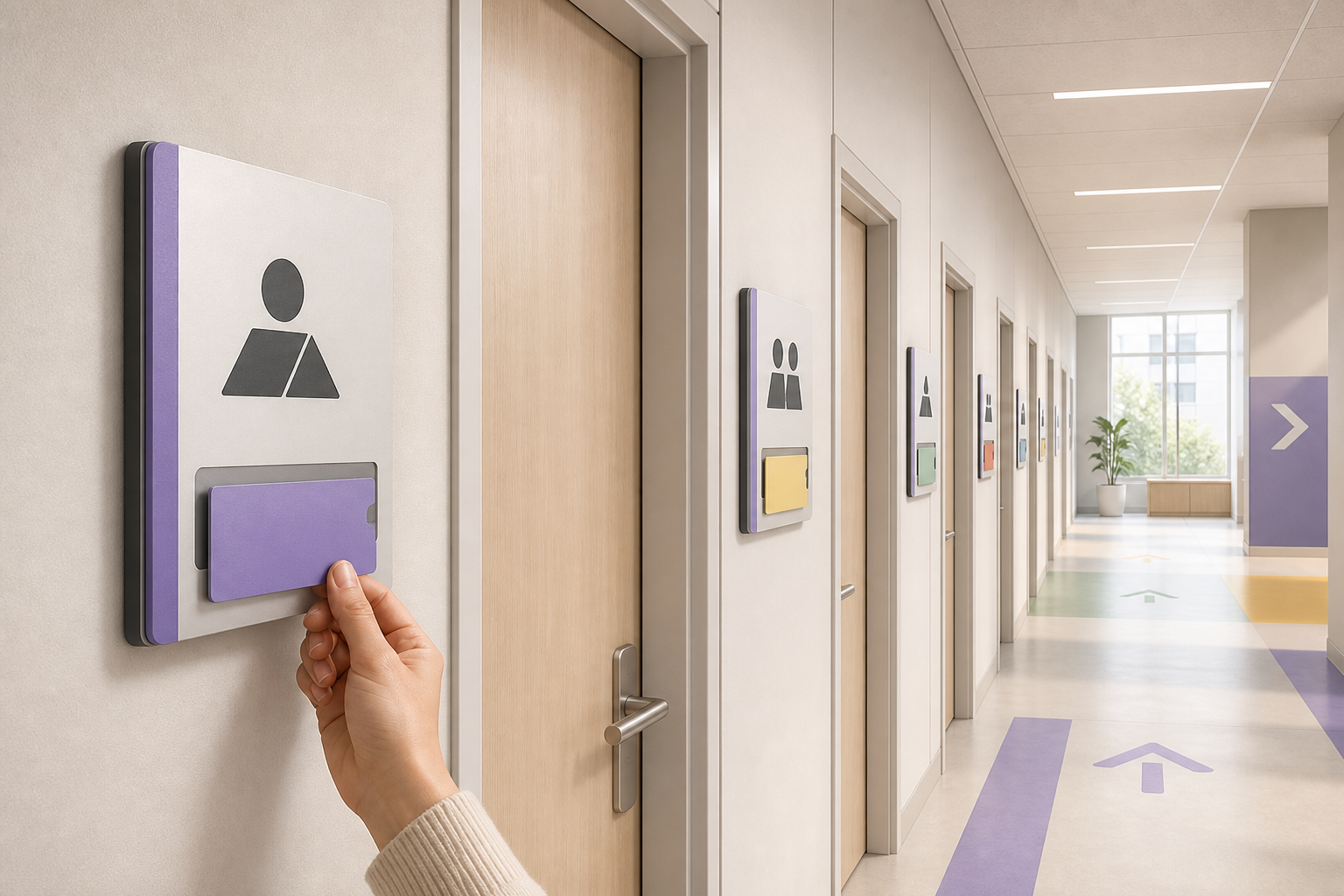
Таблички кабинетов оформляют так, чтобы посетитель сразу понял назначение помещения, легко прочитал название с расстояния и не перепутал дверь с соседней. Для этого заранее определяют текст, иерархию информации, размер, контраст, шрифт, материал и способ крепления. Ниже — практический порядок проектирования для офиса, школы, колледжа или вуза.
Зачем нужна продуманная табличка кабинета
Табличка кабинета выполняет сразу три задачи: сообщает, что находится за дверью, поддерживает навигацию по зданию и формирует визуальный образ организации. Если надпись заметна, кратка и выдержана в общей системе, человеку не приходится останавливаться у каждой двери или обращаться к сотрудникам за подсказкой. Поэтому это не просто декоративная наклейка, а элемент информационного дизайна.
Для офиса важны деловой характер, аккуратность и возможность быстро менять данные о сотрудниках или отделах. Для школы и другого образовательного учреждения на первом месте оказываются понятность, дружелюбная подача и единая логика обозначений: номер кабинета, название предмета, кафедра, лаборатория или служебная функция должны читаться одинаково на всех этажах.
Соберите систему помещений до начала дизайна
Начинайте не с выбора красивого шрифта, а с инвентаризации дверей. Составьте список всех помещений, проверьте написание названий, номера этажей и кабинетов, а также решите, какие данные должны обновляться. Такая подготовка предотвращает ситуацию, когда часть дверей оформлена по одному шаблону, а часть — случайными табличками разных размеров и цветов.
- Разделите помещения на группы: рабочие кабинеты, переговорные, классы, лаборатории, административные и технические зоны.
- Определите обязательные сведения: номер, название, должность, фамилия сотрудника или режим доступа.
- Зафиксируйте единый порядок строк, например сначала номер, затем назначение помещения, затем дополнительная информация.
- Отметьте двери, где требуется двусторонняя информация: свободно или занято, открыто или закрыто, вход для посетителей.
- Предусмотрите замену отдельных элементов, если сотрудники, кабинеты или расписание могут меняться.
Выберите размер, материал и крепление
Размер таблички зависит от длины текста, ширины дверного полотна и расстояния, с которого посетитель должен прочитать надпись. Для короткого номера кабинета достаточно компактного формата, а длинному названию отдела или кафедры понадобится больше ширины либо две строки. Не уменьшайте буквы только ради сохранения маленького размера: читаемость важнее экономии площади.
Материал выбирают по условиям эксплуатации. В сухом офисе подойдут пластик, акрил, композитная панель, металл или плотная самоклеящаяся плёнка. В школе и вузе особенно важны устойчивость к частому контакту, простота очистки и отсутствие острых краёв. Для временных мероприятий удобны картонные или пластиковые вставки, которые можно быстро заменить без переделки всей основы.
- Используйте матовую поверхность, если рядом есть окна, светильники или стеклянные двери.
- Выбирайте жёсткую основу для крупных настенных указателей и табличек в местах с интенсивным движением.
- Закладывайте безопасное крепление: ровное, устойчивое и не мешающее открыванию двери.
- Проверяйте, можно ли снять табличку без повреждения поверхности, если помещение арендуется.
- Согласуйте способ крепления с материалом двери: клей, дистанционные держатели, винты или магнитная система подходят для разных оснований.
Что выбрать для офиса
В офисе хорошо работает сдержанная табличка с логотипом или фирменным цветовым акцентом, номером помещения и названием отдела. Если кабинеты часто перераспределяются, используйте сменные вкладыши или держатели. Для переговорных можно добавить короткую строку о правилах бронирования, но не перегружать дверь расписанием, которое быстро устаревает.
Что выбрать для школы, колледжа или вуза
В образовательном учреждении полезно разделить информацию по уровням. Крупно указывают номер кабинета, ниже — предмет или функцию помещения, а дополнительной строкой при необходимости добавляют класс, кафедру или название лаборатории. Для младших школьников допустимы более выразительные цветовые акценты, но базовая система должна оставаться спокойной и понятной взрослым посетителям.
Подберите шрифт, который легко читать
Для дверных табличек подходят шрифты с ясными формами букв, достаточным межбуквенным расстоянием и хорошо различимыми знаками кириллицы. Слишком декоративный шрифт может выглядеть эффектно на макете, но стать неудобным на расстоянии. Особенно внимательно проверяйте пары похожих символов, цифры и буквы, которые могут сливаться в плотной надписи.
Используйте не больше двух начертаний в одной табличке. Например, номер кабинета можно выделить полужирным, а название помещения набрать обычным начертанием. Не растягивайте буквы искусственно и не применяйте слишком узкий кегль ради длинной фразы. Лучше сократить формулировку или перенести её на вторую строку, сохранив комфортное чтение.